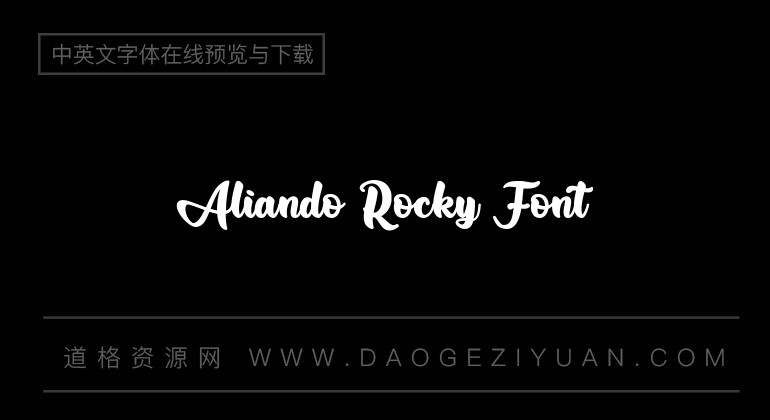
Aliando Rocky Font
Aliando Rocky Font 是一种免费的手写字体,具有非常明显的手写风格。该字体由 Aliando Syarief 设计,他是一位印尼的设计师和演员。 Aliando Rocky Font 包含大写字母、小写字母、数字、标点符号和特殊字符。它的风格非常干净和自然,适合用于各种设计项目中,特别是需要表现出亲切、温馨、手写感的场合。该字体的设计非常适合用于海报、明信片、卡片、logo、标志等项目。 Aliando Rocky Font 是一种 TTF 格式的字体,可以在 Windows 和 Mac 操作系统上使用。它可以在多种设计软件中使用,如 Adobe Photoshop、Adobe Illustrator、Sketch、Figma、Procreate 等。
Aliando Rocky Font是一款非常不错的手写艺术字体,具有很好的视觉感,适合于文化类的宣传设计、商业类品牌的广告和产品包装设计以及个性化文字排版等较多场景。